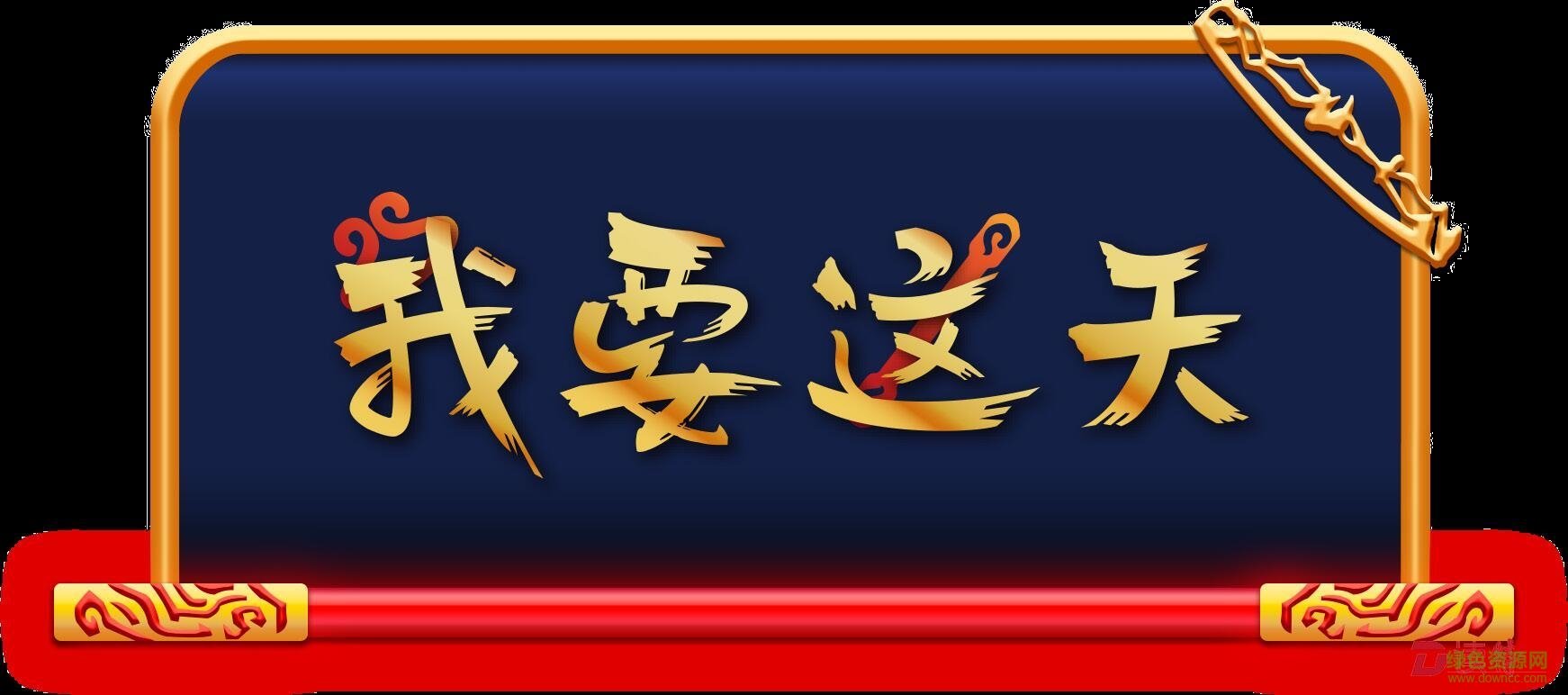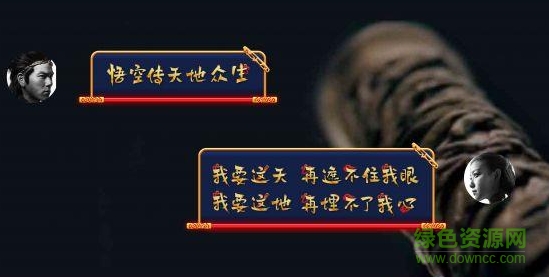
方正悟空體是方正字跡推出的一款新字體,字跡簡(jiǎn)單隨意,蘊(yùn)含著凌厲的氣勢(shì)和恣意的風(fēng)采,藍(lán)色的背景顯得光芒萬(wàn)丈和唯我獨(dú)尊,喜歡的朋友就來(lái)綠色資源網(wǎng)搶先體驗(yàn)吧!
“方正悟空體”的設(shè)計(jì)者--方正手跡設(shè)計(jì)團(tuán)隊(duì)介紹道,孫悟空的熱血、灑脫、有情有義,深深感染著數(shù)代中國(guó)人,此次希望借由文字,將這個(gè)角色的藝術(shù)魅力持續(xù)延伸。
“方正悟空體”的設(shè)計(jì)風(fēng)格取自孫悟空桀驁不馴的人物性格,并將其設(shè)計(jì)為彩色字體。黃色的主體字與充滿激情斗志的紅色掛件,深藍(lán)色背景搭配相得益彰,體現(xiàn)了悟空與其命運(yùn)抗?fàn)幍南Mc熱血燃燒的激情。